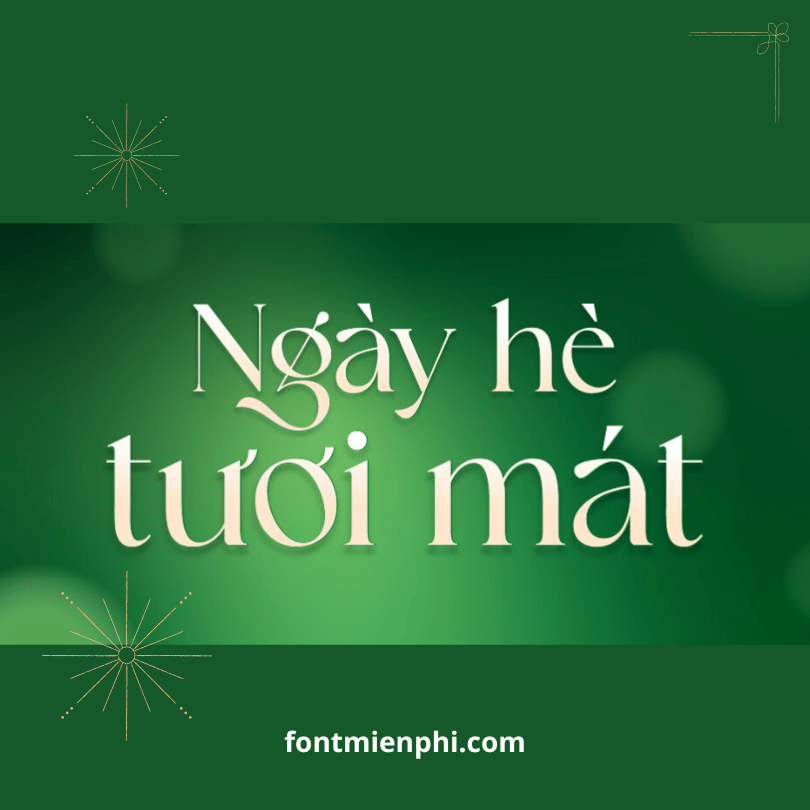
Font Việt hóa 1FTV VIP Belgan Aesthetic Regular
Font Việt hóa 1FTV VIP Belgan Aesthetic Regular – Tinh Tế & Sang Trọng
Font 1FTV VIP Belgan Aesthetic Regular thuộc bộ sưu tập cao cấp của 1FirstFont (1FTV), được thiết kế với phong cách tối giản nhưng đầy tinh tế, phù hợp cho các dự án đòi hỏi sự sang trọng và chuyên nghiệp.
Đặc điểm nổi bật:
✔ Việt hóa hoàn chỉnh – Hỗ trợ đầy đủ bảng mã Unicode, bao gồm các ký tự tiếng Việt có dấu, hiển thị sắc nét trên mọi nền tảng.
✔ Phong cách tinh tế – Nét chữ mảnh, thanh thoát với độ cân bằng hoàn hảo, mang lại cảm giác sang trọng và hiện đại.
✔ Đa dụng – Phù hợp cho thiết kế branding, tạp chí, bao bì, profile công ty, và các ấn phẩm cao cấp khác.
Ứng dụng tiêu biểu:
• Thiết kế logo & bộ nhận diện thương hiệu
• Tài liệu quảng cáo, brochure, namecard
• Ấn phẩm thời trang, nội thất, bất động sản cao cấp